“Malvinas Sans”: un diseñador creó una tipografía con la bandera que la Selección exhibió tras el partido contra Inglaterra
El rosarino Juan Manuel Pelillo, que vive en Barcelona, habilitó en sus redes sociales una tipografía de descarga gratuita ideada a partir de la leyenda “Las Malvinas son argentinas”; recibió miles de mensajes
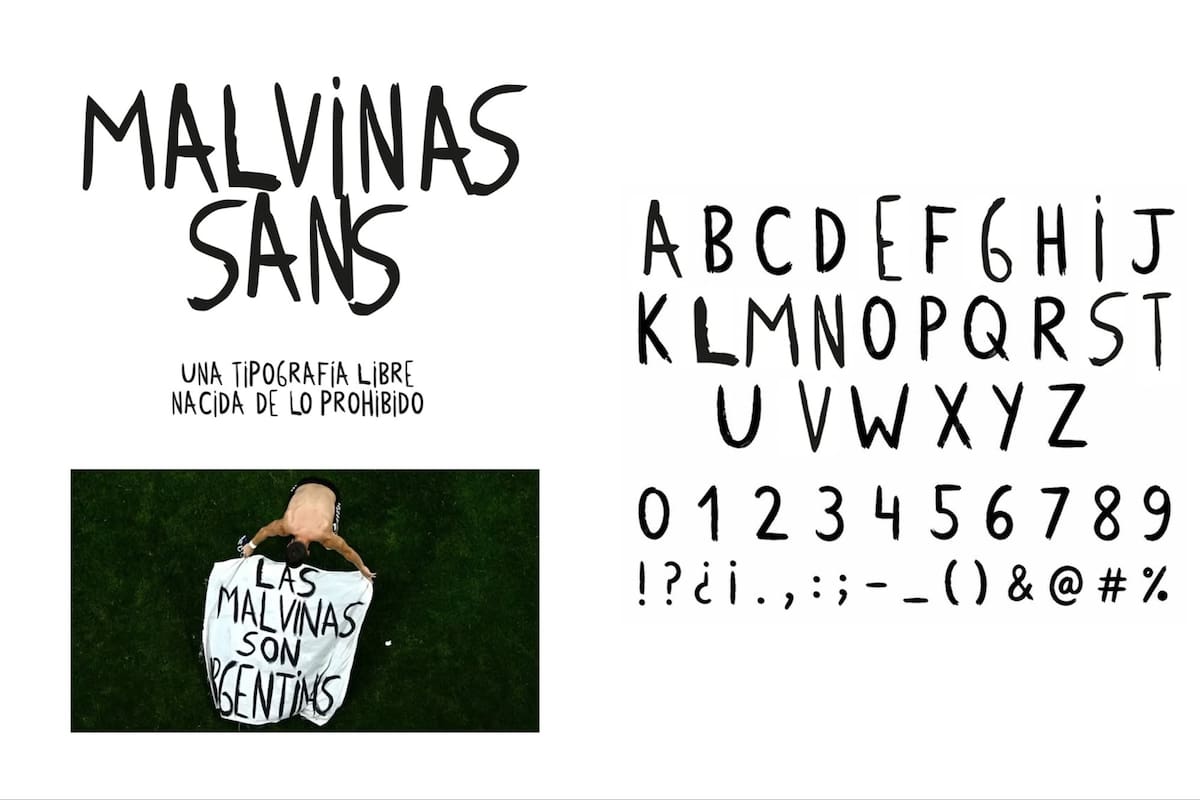
Días después del final del Mundial de Fútbol, el diseñador Juan Manuel Pelillo (Rosario, 1977) compartió en su cuenta de Instagram un enlace para descargar en forma gratuita la fuente “Malvinas Sans”, creada a partir de la leyenda de la bandera que exhibió la selección argentina tras la victoria contra Inglaterra, “Las Malvinas son argentinas”, el 15 de julio en Atlanta. Director de arte y diseñador, Pelillo reside desde 2010 en Barcelona. Después de la difusión de la tipografía, empezó a recibir miles de mensajes de agradecimiento de argentinos en la “diáspora” y en el país.
“Una tipografía q nace de lo prohibido. Dijeron que el fútbol no era político. Pero esta frase va mucho más allá del fútbol. ‘Las Malvinas son Argentinas’ es memoria, identidad y una forma de volver a poner en discusión la soberanía de un país. No celebra una guerra absurda. Recuerda que la historia sigue abierta. Porque prohibir una frase no termina un debate. A veces, lo vuelve más necesario”, escribió en la publicación de Instagram (en español y en inglés) que ya tiene más de 57.000 “me gusta”.
En diálogo con LA NACION, Pelillo confirma que la idea de crear la tipografía le surgió después del partido de semifinales, “cuando a alguien se le ocurrió entrar al estadio con una bandera con un mensaje prohibido, dársela a los jugadores y que los jugadores la desplegaran ahí en el medio del campo de juego y que millones, miles de millones de personas vieran el mensaje”. Ningún expediente de la FIFA podrá borrar la escena.
“En ese momento sentí que algo muy poderoso estaba pasando: me detuve a ver no solamente el mensaje y el contenido, sino también la forma a nivel de diseño -cuenta-. Un diseño que me recordó muchísimo a la portada del Nunca Más y a la potencia que tiene esa portada”.
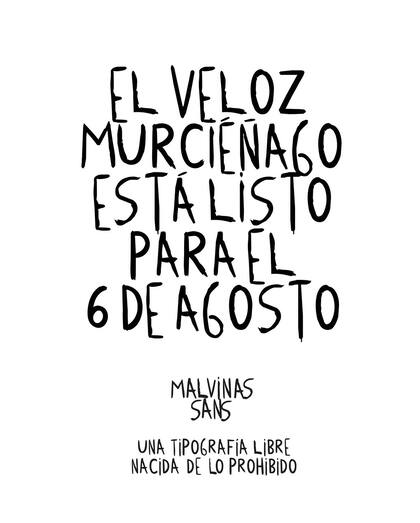
“Eso me quedó en la cabeza y pensé en por qué no homenajear ese momento desde mi lugar, completando las letras que faltaban, digitalizarlas y compartir la tipografía para que todo el mundo la pueda descargar gratis desde cualquier ordenador o desde su móvil. Ojalá se use para escribir más mensajes así, poderosos y de protesta, para que cuando tengas algo que decir lo puedas escribir con ella”. Varios mensajes circulan en ese sentido, no solo en redes sociales.
¿Es un proyecto sobre Malvinas? “Creo que sí, que lo es, pero no únicamente –responde–. Es un proyecto que también va sobre la memoria, sobre la identidad y sobre cómo el diseño puede participar de conversaciones que aún siguen abiertas, porque en este caso no intentaba glorificar una guerra. La guerra es terrible, es una tragedia. Lo que permanece es la discusión sobre la soberanía, sobre la historia y sobre la memoria colectiva. Esa bandera logró que se volviera a hablarse del tema y mi intención es que con esta tipografía se pueda también seguir hablando del tema y de otros temas también importantes”.
Como queda claro, no quiso generar una tipografía comercial. “Lo que quise es conseguir y respetar el trazo del original, que fue a puño, pintado sobre una sábana –explica–. Esas características no las quise perder y no se perdieron”.
No esperaba la repercusión que tuvo “Malvinas Sans”. “Es una sorpresa absoluta –admite–. Pensé que iba a interesar dentro del mundo del diseño, pero terminó llegando a periodistas, a excombatientes, a docentes, a ONG, a gente que ni siquiera trabaja en áreas creativas. Ahí es cuando empiezo a darme cuenta de que este proyecto deja de ser mío para convertirse en una herramienta cultural”.
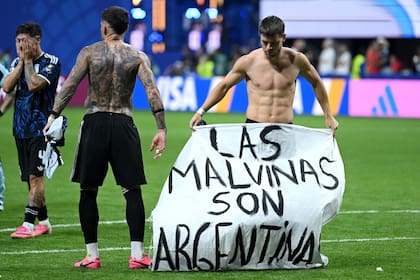
“Una de las razones de la repercusión es porque esta tipografía nace de lo prohibido –afirma–. El proyecto seguramente no existiría si esa bandera no hubiese sido censurada. Muchas veces, cuando intentás prohibir una expresión, ocurre exactamente lo contrario y adquiere todavía más fuerza. La tipografía nace de ese intento de silenciar un mensaje y por eso lo que propone es una forma de mantener vivo ese mensaje”.
“A veces me pregunto si lo que está pasando es realmente político –reflexiona–. Este proyecto no habla de una política partidaria, sino de memoria, identidad y diseño, lo que lo convierte en político. Como el fútbol, que decían que no era político. Y vuelvo al diseño: siempre tuvo la capacidad de registrar momentos importantes de una sociedad. En este caso, simplemente tomó una escritura que nació de una bandera y la convirtió en una herramienta para que esa conversación pueda seguir existiendo”.